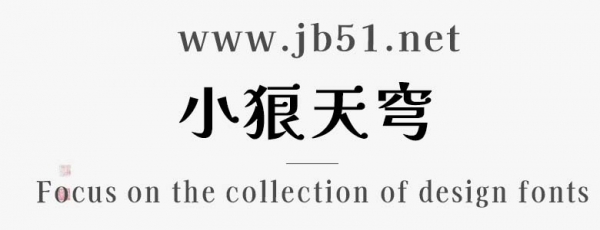
小狼天穹是一款不錯的藝術(shù)字體,字體筆觸適中,字形端正,具有很好的視覺感,適合應(yīng)用于藝術(shù)設(shè)計、平面宣傳設(shè)計、網(wǎng)頁設(shè)計,書法字帖等領(lǐng)域,需要的朋友可以前來本站下載。
小狼天穹是基于日本[ 解星計劃」開發(fā)的「解星」字型的衍生字型。 以參照傳承字形檢校表修改的「宇文天穹」字體為基礎(chǔ),補制欠缺的繁簡體字和注音符號。